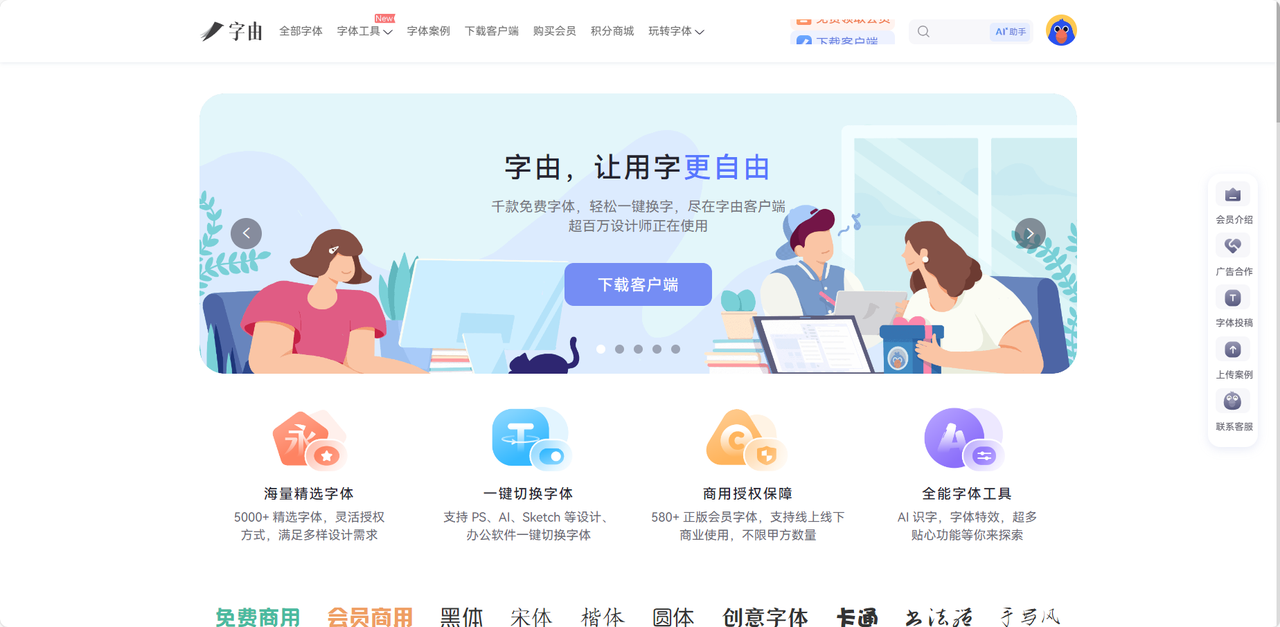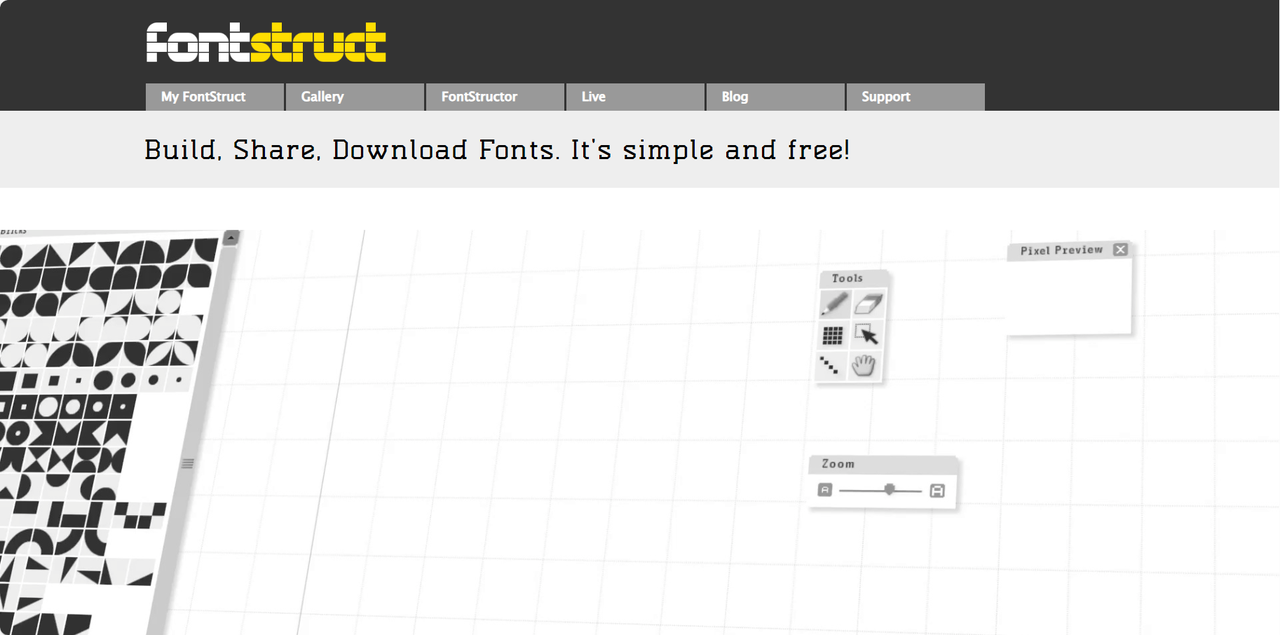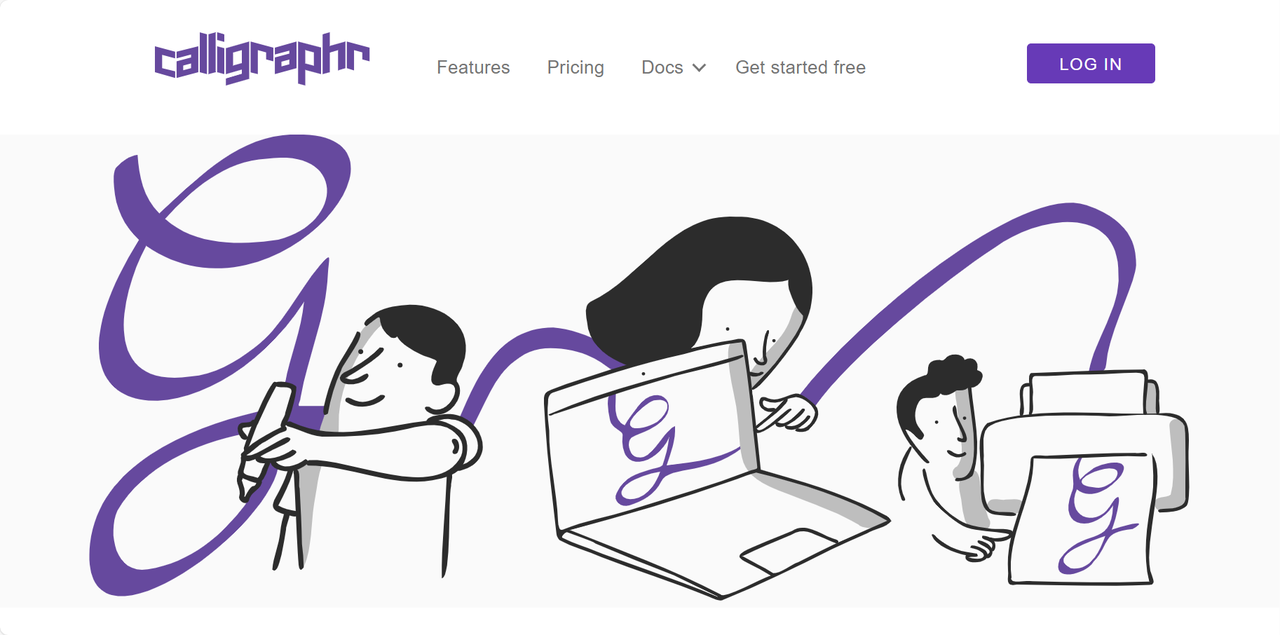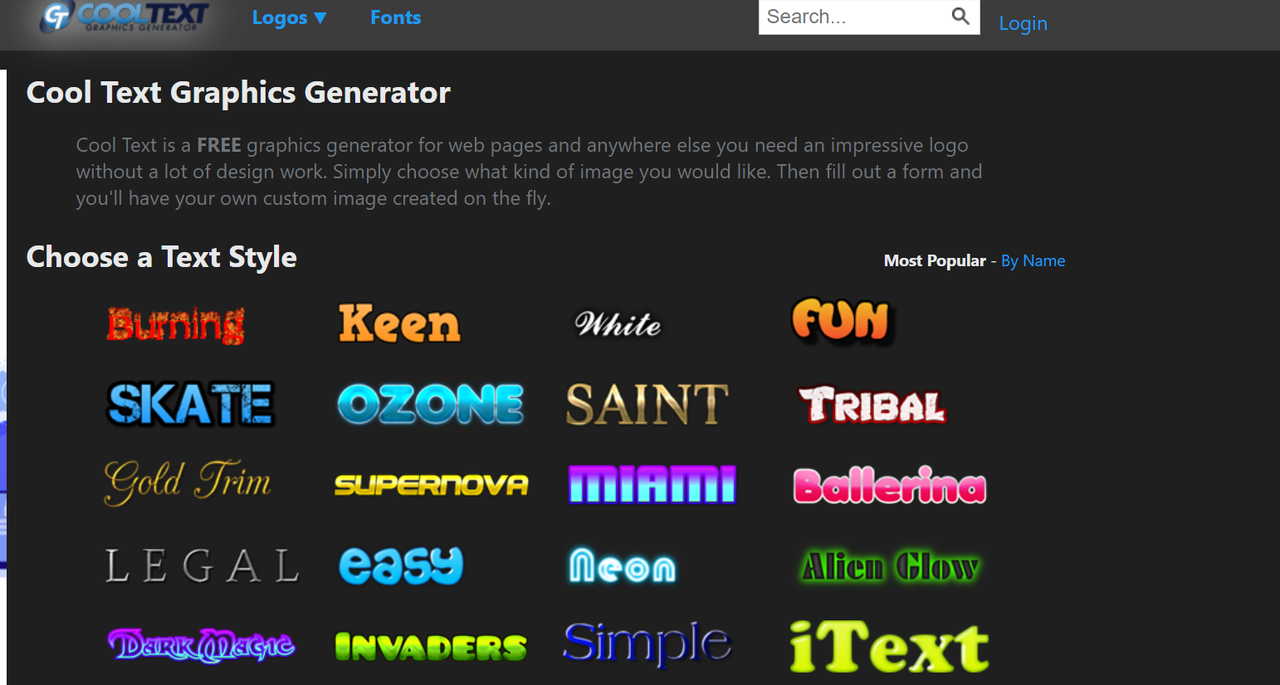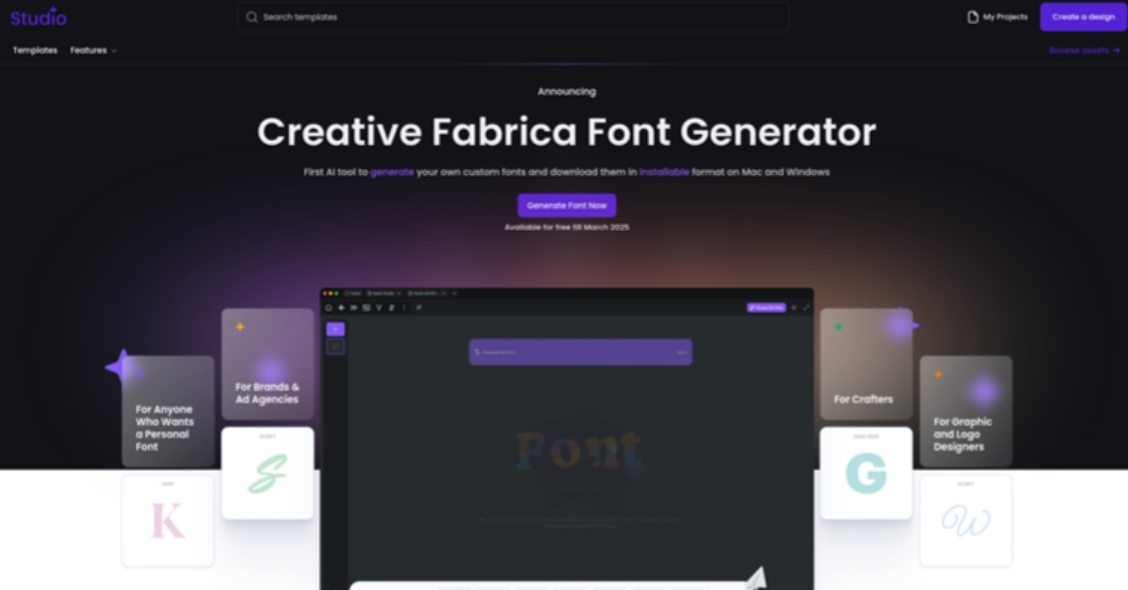
全网热门在线字体生成工具,各种风格字体一键生成
总觉得作品里的文字不够出彩?总是找不到满意的字体?以往我们想要获得个性化的字体,需要花大把时间学习文字设计、花大量金钱购买设计软件,如今我们只需要用在线字体生成工具就可以轻松解决这些问题。打开浏览器,挑选心仪的字体风格,输入文字,几秒钟就可以在线生成专业级的字体,还能直接复制或下载保存,不需要安装任何软件,不需要掌握多么高超的设计能力,零门槛就能让文字变得更加有光彩夺目。今天这篇文章就给大家整理了一些全网热门的在线字体生成工具,你想要的风格这里统统都有,满足日常创作和专业设计的双重需求。
一、字由
字由是国内设计师群体中使用率极高的一款字体管理工具,收录了海量正版的字体资源,涵盖宋体、黑体、手写体、书法体、创意字体等多种类型,还能在线预览字体效果,只需要输入文字就能即时查看。对于日常需要频繁使用不同字体的用户来说,字由绝对是最高效最便捷的工具。
最值得一提的就是字由的 AI 字体功能,用户只需要挑选一个自己喜欢的字体模板,输入文字内容,AI 就会自动生成该风格的字体,即使是新手小白也能快速上手使用。生成的字体文件可以下载为透明背景的图片格式,后续用于 PS、XD、Sketch 等设计软件二次创作也非常方便呢。
二、FontStruct
FontStruct 不是传统意义上的字体资源平台,也不是 AI 生成工具,它提供了在线生成字体的全套工具链,只不过这个过程需要你自己动手来搭建字体。实际上也就是说,FontStruct 是让用户使用内置的网格系统和几何形状模块,像搭积木一样设计每一个字母。同样不需要你掌握很强的设计能力,不用花费大量时间学习,你只需要在该平台上布置方块,通过不同的排列组合创造出每个字体,比较适合用来生成像素风字体或创意字体。除此之外,FontStruct 也是一个庞大的设计社区,有很多用户会在上面分享自己制作的字体作品,大家可以互相交流学习,某些时刻还能让自己获取更多设计灵感哦。
三、Calligraphr
如果说大部分工具都是直接给你提供字体模板,那么 Calligraphr 就是帮助你亲手创造属于自己的字体,核心优势就是将你的手写笔迹转化为可安装使用的字体文件。你只需要在官网下载一份模板打印出来,然后书写常用的字母、数字以及标点,然后拍照再上传到官网,Calligraphr 会自动识别每个字符并生成对应的字体文件,真正生成属于你自己书写风格的字体。最关键的是,这款工具支持你对每个字符进行精细化调整,确保最终生成的祝福看起来更加舒服自然。付费版本还提供了更进阶的功能,比如字体变形功能可以为一个字符设计不同写法,输入文字内容后随机交替生成新字体;或者连笔字功能也会让字体更加贴近手写化。
四、Cool Text
想要快速获得一个酷炫风格的文字,Cool Text 一定是最佳选择。这是一个深受设计行业多年好评的在线字体生成工具,最大的特色就是将普通文字转换成具有立体感、霓虹光感等视觉冲击力强的文字 适合用于电影标题、电竞 LOGO、游戏主界面等场景下。虽然是国外的网站,但是界面布局清晰且操作简单,用户进入网站后,输入文字并挑选你喜欢的字体特效风格,点击生成按钮就能快速获得新的字体。使用门槛几乎为零,非常适合没有平面设计基础但对视觉呈现有要求的用户。不过需要注意的就是,Cool Text 在线生成的文字是以图片形式直接保存的,不是可以编辑的字体文件,这也就意味着它适合用于一次性图文设计。如果你经常需要批量替换文字内容,或者需要生成长文本,这款工具可能不太适合你。
五、Creative Fabrica Font Generator
最后来和大家介绍一下 Creative Fabrica Font Generator,凭借强大的 AI 技术,内置海量字体数据,成为了在线字体生成工具中的新秀之一。用户登入该网站之后,只需要选择想要的字体风格,AI 就会自动生成一套风格统一的字体包供大家下载。我觉得非常好用的一点在于,如果你在实时预览过程中对某个单独的字符不太满意,它支持在线进行局部重新生成和调整哦,非常高效且便捷。由于 Creative Fabrica Font Generator 在创立之初被输入了字体设计的规律以及美学特征,所以用它生成的字体几乎不会和其他作品撞型,原创性很高,又省时省力。另外,Creative Fabrica Font Generator 的下载格式对于创作者来说非常友好,可以直接下载 ttf 格式的文件,后续直接安装到 Mac 或 Windows 电脑上使用,同时这套字体可以获得个人使用和商业使用的双重授权,因为这是你自己生成的字体。
怎么样?是不是已经发现了在线字体生成工具的魅力所在。字由是提供 AI 字体功能的一站式字体管理工具;FontStruct 让你像玩积木一样搭建字体;Calligraphr 为你打造独一无二的手写字体;Cool Text 主打生成视觉冲击力强的特效字体;Creative Fabrica Font Generator 利用AI模型生成定制设计感字体,总有一款工具适合你。一键生成字体的时代已经到来,让平淡的文字“活”起来,更加大胆热烈地去发挥你的创意,跟我一起动手体验一下这些工具吧。